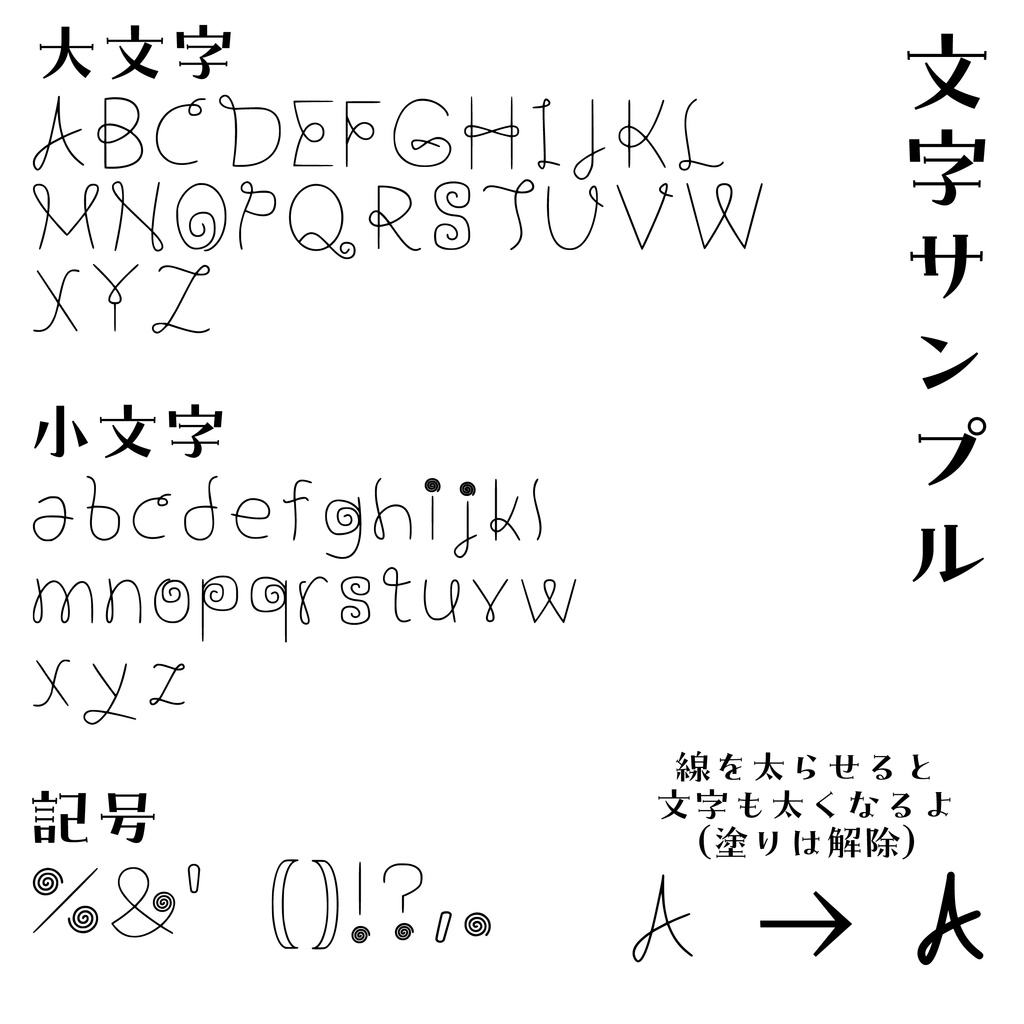
【無料】Mix Swirl Font
*MixSwirlFontについて* 京都・二条にあるミックスジュースのお店「Corner Mix」を イメージしたフォントです。「まぜると、きっとうまくいく!」 というお店の合言葉を落とし込んだぐるぐるミックス!な フォントになっています。 *収録文字* 英語、数字、一部記号【()!?%&',.@】 *このフォントはフリーフォントです* 【商用可能!】【改変での再配布可能!(条件あり)】